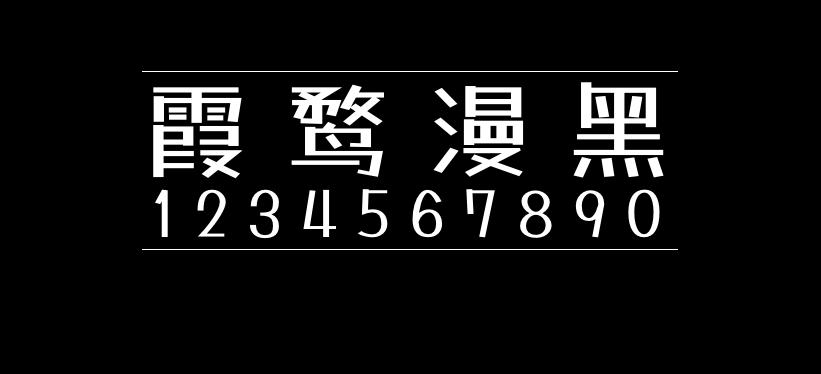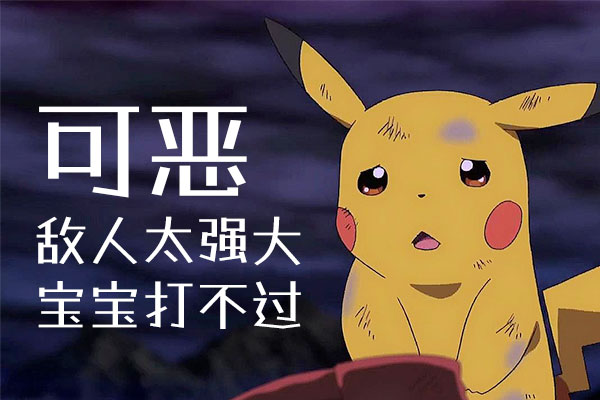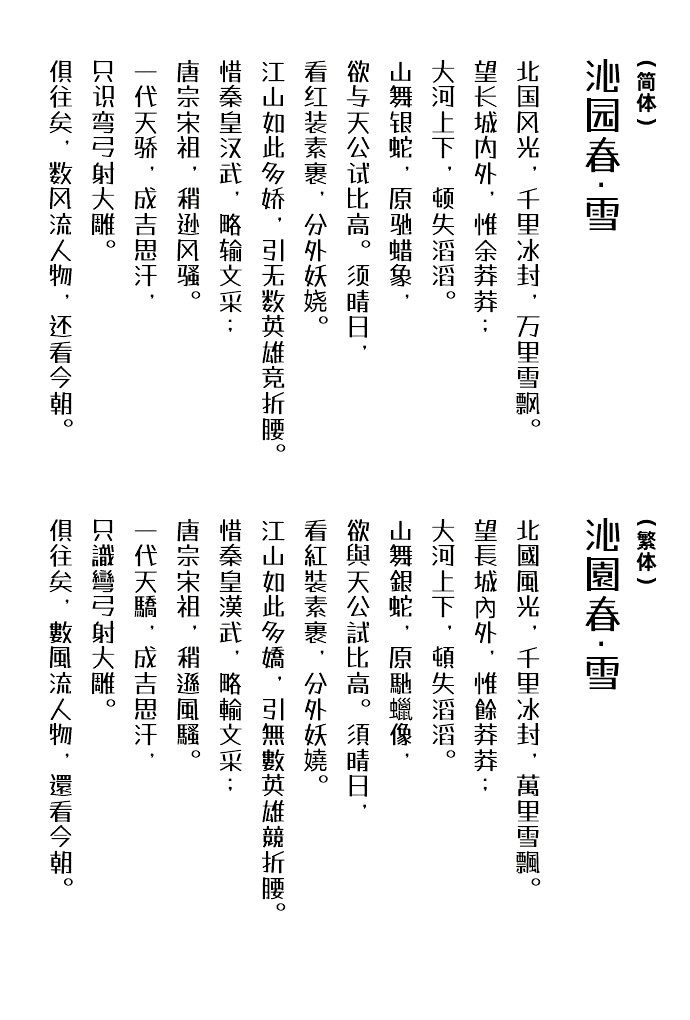
霞鹜漫黑
霞鹜漫黑是一款基于 Tanugo手写体(たぬゴ角版)衍生的开源中文字体。该字体是一款拥有马克笔书写风格的中文字体,可用于漫画、广告等用途。目前在原有日本的JIS 第一/二水准字库的基础上,增补完原字体中所含的繁体字对应的简体字,及 3500 常用字。
该字体简体部分已补齐标准6763字,繁体部分补完台湾 4808 常用字 (常用国字标准字体表);